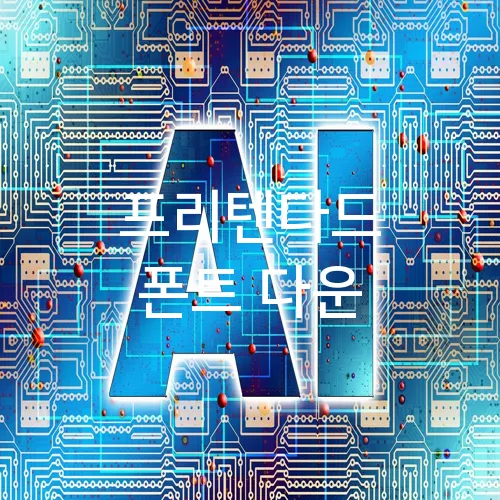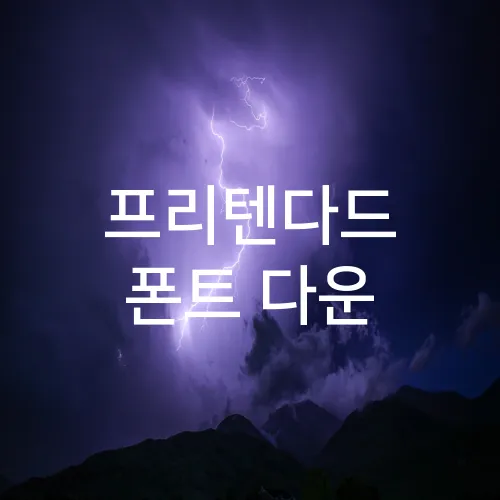
프리텐다드 폰트를 무료로 안전하게 다운로드 받으려면 몇 가지 주의할 점이 있습니다. 프리텐다드 폰트는 다양한 디자인 프로젝트에서 인기 있는 폰트로, 간결하면서도 세련된 디자인을 제공합니다. 이 폰트를 다운로드 받으려면 정식 경로를 통해 얻는 것이 중요합니다.
프리텐다드 폰트를 다운로드하고 설치하는 방법은 간단하지만, 올바른 경로를 통해 안전하게 다운로드하는 것이 중요합니다. 공식 채널을 활용하여 손쉽게 설치를 마치고, 다양한 디자인 프로젝트에 활용해보세요.
4. 자주 묻는 질문: 폰트 사용 시 주의사항 및 해결 방법
프리텐다드 폰트 사용 시 주의사항
프리텐다드 폰트를 설치한 후에도 사용할 때 몇 가지 주의해야 할 점이 있습니다. 첫째, 사용하고자 하는 목적에 맞는 상업적 사용 권한을 확인해야 합니다. 프리템포와 같은 사이트에서는 무료로 제공되는 폰트일지라도, 상업적으로 사용하기 위해서는 별도의 라이선스를 요구할 수 있습니다.
둘째, 파일 다운로드 및 설치 시 악성 코드나 바이러스 감염에 주의해야 합니다. 신뢰할 수 있는 출처에서 폰트를 다운로드하여 PC와 데이터를 안전하게 보호하는 것이 중요합니다.
셋째, 설치된 폰트를 문서나 그래픽 프로그램에서 사용할 때는 해당 프로그램의 호환성을 점검하십시오. 일부 프로그램에서는 폰트가 제대로 표시되지 않거나 기능하지 않을 수 있습니다.
– 상업적 사용 여부 사전확인
– 악성 코드 감염 주의
– 호환성 점검 필요
문제가 발생할 경우의 해결 방법
폰트를 설치한 후 문제가 발생했을 때, 먼저 설치된 폰트를 삭제한 후 재설치하시기 바랍니다. 폰트 관리자나 시스템 설정에서 폰트를 삭제할 수 있습니다. 설치 중 오류가 지속된다면 공식 지원 커뮤니티나 FAQ를 참조하여 해결 방법을 확인하시기 바랍니다.
또한, 특정 환경에서 폰트가 제대로 작동하지 않는 경우, 운영체제와 소프트웨어의 업데이트를 통해 문제를 해결할 수 있습니다. 프로그램의 최신 버전을 사용하면 호환성 문제가 줄어듭니다.
– 폰트 삭제 및 재설치
– 공식 지원 커뮤니티 참고
– 운영체제 및 소프트웨어 업데이트
이러한 과정을 통해 프리텐다드 폰트를 보다 안전하고 효율적으로 사용할 수 있습니다. 필요한 경우 추가적인 고객 지원을 받을 수도 있습니다.
5. 후회 없는 선택, 프리텐다드 폰트의 활용 팁
프리텐다드 폰트 특징 및 장점
프리텐다드 폰트는 현대적이면서도 세련된 느낌을 주는 서체로, 다양한 프로젝트에 적합합니다. 누누히 강조되는 가독성과 다양한 굵기의 폰트 스타일은 웹 디자이너와 그래픽 디자이너들 사이에서 인기가 높습니다. 나눔고딕, 배달의민족과 같은 폰트와는 차별화된 독창성을 자랑하며, 인쇄물이나 디지털 광고에 활용되기도 합니다.
– 다양한 굵기: 얇은 체부터 두꺼운 체까지 다양한 굵기를 제공하여, 사용자의 필요에 따라 선택할 수 있습니다.
– 다국어 지원: 한글뿐만 아니라 다국어 지원이 가능하여 글로벌 프로젝트에도 적합합니다.
– 깔끔한 디자인: 직관적인 글자 디자인으로 문서와 프레젠테이션에 활용하기 좋습니다.
최적의 활용 방안
프리텐다드 폰트를 효과적으로 사용하려면, 우선 어떤 매체에 활용할 것인지를 결정하는 것이 중요합니다. 인쇄 매체에서는 나눔고딕과 함께 비교하여 사용했을 때, 서로의 장점을 살릴 수 있습니다.
– 인쇄 매체: 책자, 브로슈어, 포스터
– 디지털 매체: 웹사이트, 전자책, 앱 인터페이스
카페24에서 지원하는 다양한 테마와 조합하면 블로그나 쇼핑몰과 같은 플랫폼에서 좀 더 눈에 띄는 디자인을 구현할 수 있습니다. 특히, 블로그 제목과 본문에 변화를 줄 때 사용하면 통일된 디자인 요소를 유지하면서도 다양한 느낌을 줄 수 있습니다.
활용 시 유의사항
프리텐다드 폰트를 사용할 때는 반드시 라이선스를 확인하시기 바랍니다. 대부분의 폰트는 비상업적 용도로 무료로 제공될 수 있지만, 상업적 용도로 사용할 경우에는 별도의 라이선스를 구매해야 할 수 있습니다.
– 라이선스 확인: 상업적 용도 시 구매 필요
– 무료 배포 폰트: 비상업적 프로젝트에서 활용 가능
카카오프렌즈나 두산베어스 폰트와 결합해 개성을 더할 수 있지만, 다른 폰트와 조화롭게 사용해야 시각적 혼란을 피할 수 있습니다. 결론적으로, 프리텐다드 폰트는 다양한 매체에서 감각적인 표현을 가능하게 해주는 강력한 도구입니다.
6. 프리텐다드 폰트 다운 운용의 마무리: 성공적인 설치 후 점검 사항
프리텐다드 폰트가 여러 페이지에서 응용 프로그램에 제대로 작동하는지 검토하세요. 웹 페이지 및 인쇄물에 적용할 때 부드럽고 또렷하게 보이는지 확인하는 것이 중요합니다. 이를 위해:
– 다양한 크기에서 읽기 편한지를 확인합니다.
– 여러 종류의 배경색에 대비하여 명확하게 보이는지를 체크합니다.
폰트를 적시에 업데이트하는 것도 필수적입니다. 폰트 라이브러리를 제공하는 사이트에서 버전 업데이트 정보를 자주 확인하여 최신 상태로 유지해야 합니다.
폰트 활용 아이디어
프리텐다드 폰트를 활용하여 전문적이고 고급스러운 인상을 줄 수 있습니다. 회사 프레젠테이션, 브로셔, 웹 사이트 등 다양한 분야에서 디자인의 통일성을 유지하면서 가독성을 높일 수 있습니다.
– 회사 로고에 사용하여 브랜드 이미지를 강화합니다.
– 중요한 문서를 인쇄할 때 시각적 매력을 더합니다.
각 프로젝트에 적합한 방법으로 폰트를 활용하면 디자인 효과가 향상됩니다. 다양한 예제와 조언은 전문 디자인 관련 커뮤니티에서 얻을 수 있습니다.
폰트 사용과 관리의 세심한 계획을 통해 더욱 효과적이고 매력적인 디자인 결과물을 만들어보세요.